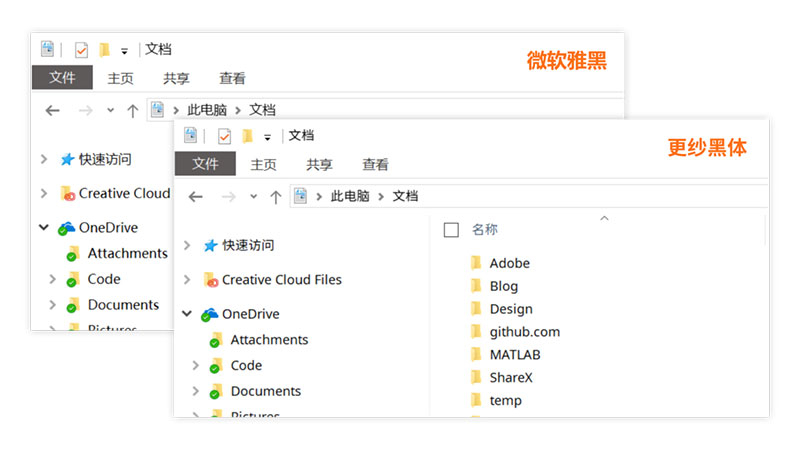
更纱黑体(Sarasa Gothic),一款在 100% 缩放比例下有着优秀渲染效果的字体,一种基于 Inter、Iosevka 和 思源黑体 的 CJK 复合字体,开源免费。
更纱黑体提供了多种字形风格、字重的组合,以满足不同的场景和需求:
更纱黑体的西文字符基于 Inter 字型设计。
Gothic:标准字型;全宽引号。
UI: 专为UI界面设计的字型,半宽引号。
Slab: 粗衬线体,在原字形基础上增加了 Slab serif 的特征,使其更具有辨识度。
连字 (Ligature) 遇到特定连续的字符时会进行组合,优化阅读体验。在编程语言中,连字特性也能让数学运算符号更容易的阅读。
根据特定语言和地区主要使用的字形来选择字体:SC: 简体中文、TC: 台湾繁体中文、HC: 香港繁体中文、CL: 传统旧字形、J: 日文、K: 韩文。
上图是一个对比,不过因为电脑是 2K 分辨率的屏幕,其对比并没有很明显,更多是字型上的差别,但是如果将电脑外接 1080p 分辨率的显示器的时候,两种字体的显示效果差别就很是明显了。总之,更纱黑体相比微软雅黑在 100% 缩放比例下的显示效果确实要好上一些。